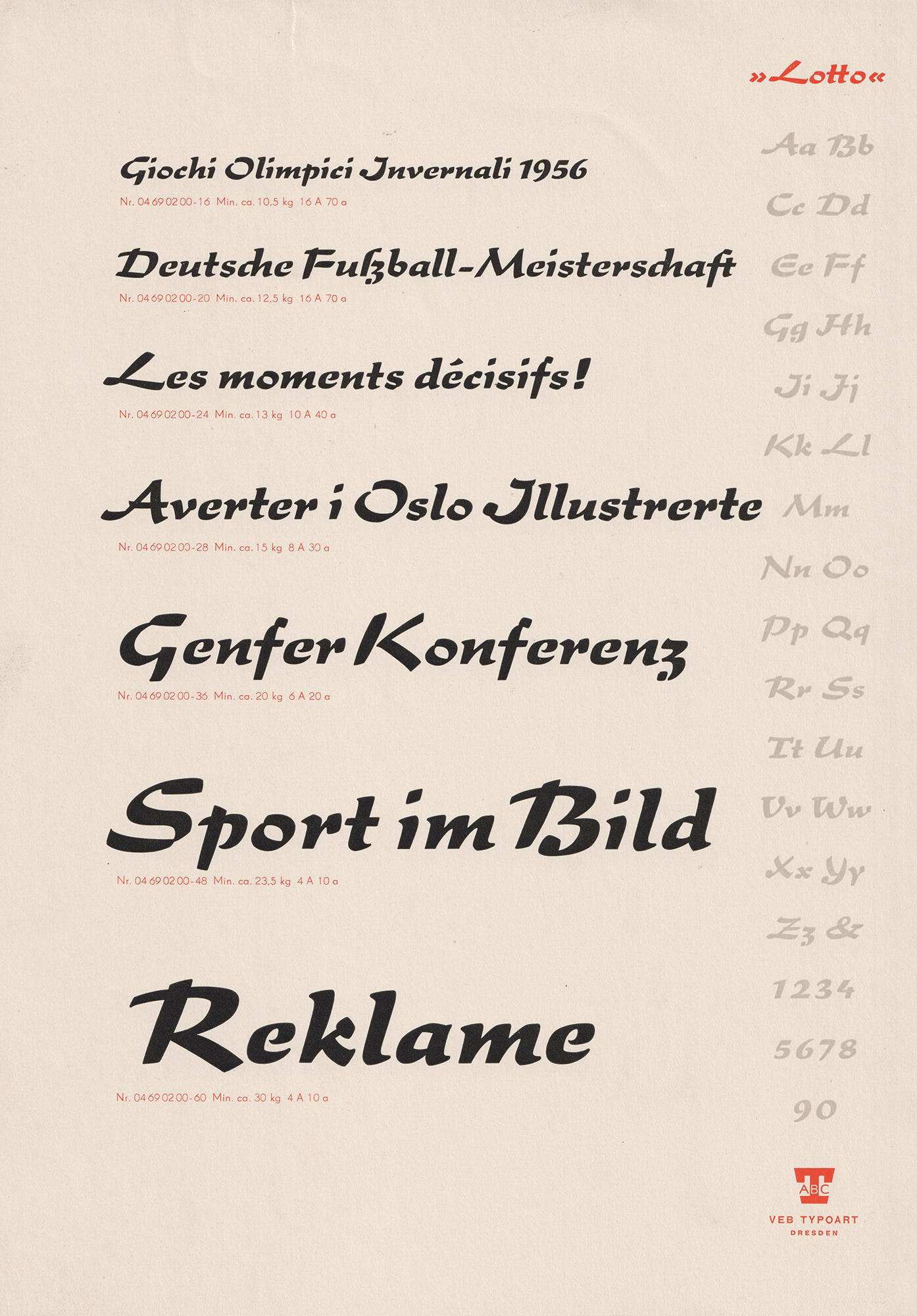
Font-Wiki: Lotto
Die Lotto ist eine schwungvolle Pinselschrift von Herbert Thannhaeuser und erschien ursprünglich 1955 bei Typoart. 2009 kam eine Digitalisierung von CanadaType heraus.
Original-Bleisatzmuster von Typoart